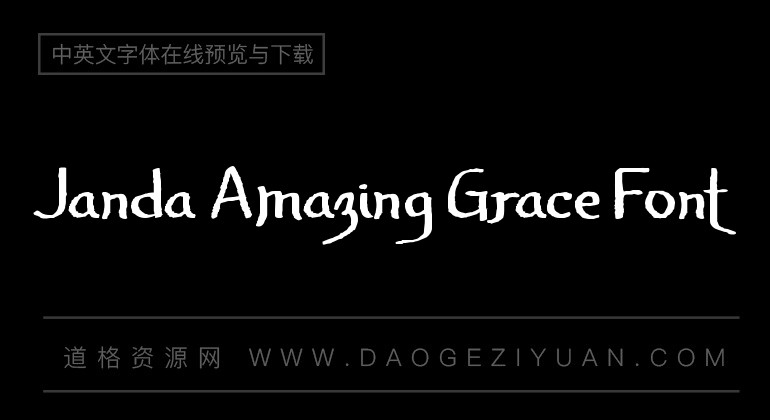
Janda Amazing Grace Font 是一种手写字体,由 Kimberly Geswein 设计。它的风格非常自然、轻松,适用于各种场合,比如手写便签、海报、贺卡、书信等等。 这种字体的特点是流畅、有节奏感,字母之间的距离比较宽松,字母大小也不规则,让人感觉非常有生命力。它的笔画非常有特点,有些地方比较粗,有些地方比较细,非常适合用在需要表达人情味的文字上。同时,这种字体也非常容易辨认,适合用在标题或者标语等需要突出性的地方。 总的来说,Janda Amazing Grace Font 是一种非常灵活、自然的手写字体,给人留下非常愉悦的印象。内容介绍
Janda Amazing Grace Font是一款非常不错的手写艺术字体,具有很好的视觉感,适合于文化类的宣传设计、商业类品牌的广告和产品包装设计以及个性化文字排版等较多场景。